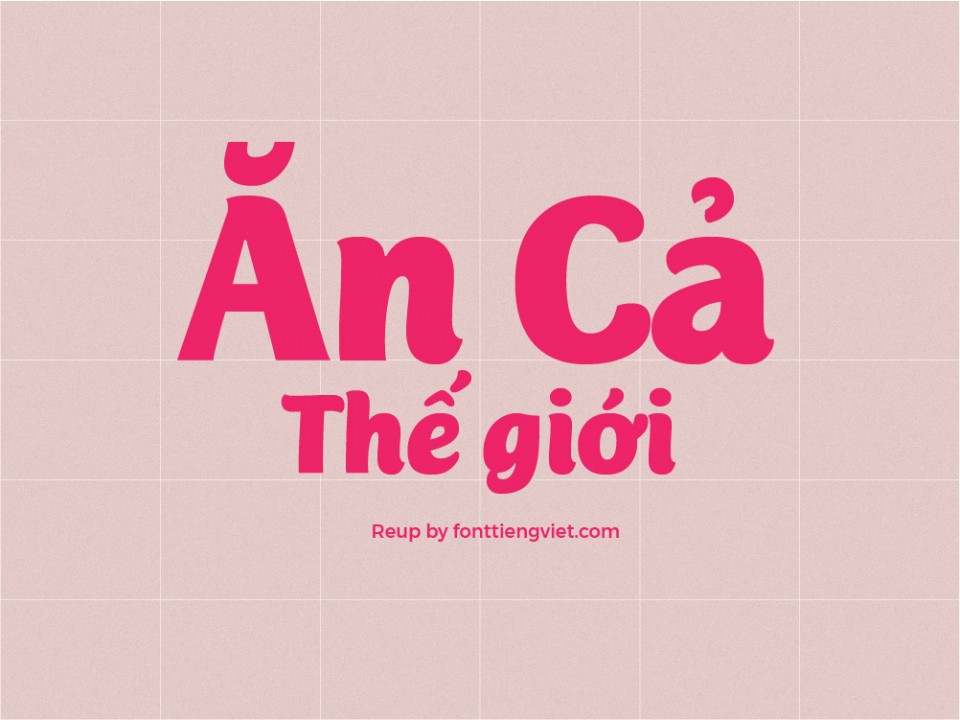
Giới thiệu về Font việt hóa iCiel Mijas – Ultra
Trong thế giới đồ họa hiện đại, việc tìm kiếm một Font Miễn Phí chất lượng luôn là ưu tiên hàng đầu của các bạn học sinh và nhà thiết kế trẻ. Font việt hóa iCiel Mijas – Ultra nổi bật như một giải pháp hoàn hảo cho những dự án đòi hỏi sự mạnh mẽ nhưng vẫn giữ được nét tinh tế riêng biệt. Đây là bộ phông chữ thuộc phong cách display với đường nét dày dặn, giúp thông điệp của bạn trở nên nổi bật ngay từ cái nhìn đầu tiên trên các banner hay tiêu đề báo chí.
Đặc điểm nổi bật của Font việt hóa iCiel Mijas – Ultra
Phiên bản Ultra của dòng Mijas mang đến một trọng lượng cực lớn, tạo cảm giác vững chãi và uy quyền. Điểm đặc biệt nhất là toàn bộ các ký tự đã được iCiel tối ưu hóa hoàn toàn cho tiếng Việt, giúp người dùng không còn lo lắng về lỗi hiển thị dấu câu. Sự kết hợp giữa những đường cong mềm mại và các góc cạnh dứt khoát làm cho bộ chữ này trở nên linh hoạt trong nhiều bối cảnh khác nhau từ trang trí thiệp mời đến làm slide thuyết trình học tập.
Cách sử dụng Font việt hóa iCiel Mijas – Ultra hiệu quả
Để tận dụng tối đa vẻ đẹp của bộ chữ, bạn nên kết hợp nó với các phông chữ không chân (sans-serif) nhẹ nhàng nhằm tạo sự tương phản. Phông chữ này cực kỳ phù hợp cho các tiêu đề lớn, bìa sách hoặc thiết kế logo thương hiệu cá nhân. Lưu ý không nên sử dụng cho các đoạn văn bản dài vì độ dày lớn có thể gây mỏi mắt cho người đọc.
Kết luận về bộ chữ iCiel Mijas